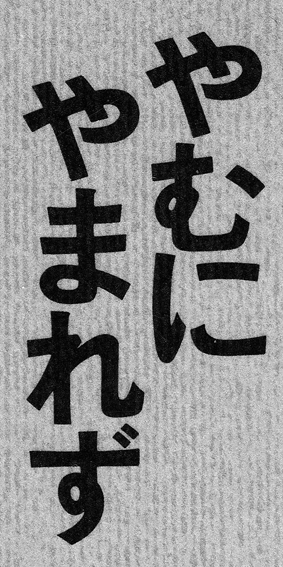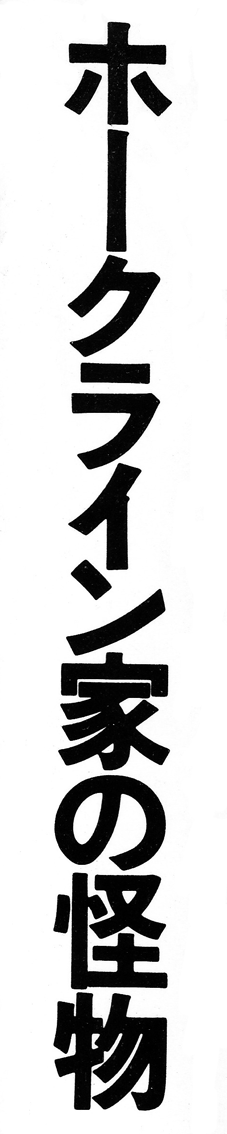
かな民友ゴシック
ああ、こまった。
いったいなにがこまるのかって、この書体についてかこうとするとき、〈かな民友ゴシック〉の名前だけを挙げるのはひどくきまりが悪いからだ。
私は今まで〈かな民友ゴシック〉について写研の写植書体だという程度の知識しか持ち合わせていなかったのだが、もともとは民友社という活版製造所の活字書体を写研が写植化したものだそうだ。ちなみにモリサワにも同じ民友社の名前を冠した写植書体がある。
しかし現在、巷に流通しているこれとよく似た文字は〈ヒラギノ角ゴオールド〉という名前のデジタルフォントで、それは民友社とはまた別の、藤田活版製造所の金属活字を見本に字游工房が制作した〈游築初号ゴシックかな〉と、以前からあった〈ヒラギノ角ゴシック〉の漢字を組み合わせて、大日本スクリーン製造からリリースされた新しい書体だという(ああ、こまった。なんのこっちゃである)。
こんなややこしいことになったのも、字形というものの宿命だなあと思うのだが、民友社、また藤田活版製造所のいずれも、明治時代に日本の活版印刷技術を牽引した東京築地活版製造所の活字母型を継承しているためらしい。
このとぼけた味わいをもつゴシック体が、時空を超えて同質性を保っている、という事実は、日本の活字書体のデザインがいかに極められていたかということの証明にも思えてぐっとくる。
勿論、読者にとっては文字の血統や素性を知る必要などないし、目の前で組まれたものがすべてだ、とも思う。
だから正直に告白すれば、私は、この書体に対して、まるでサンドウィッチマンのようなイメージをもっていた。目立つ図体のわりに肩身がせまそうというか、一歩引いている、というか。
活字だったころの名残りというべきか、文字の全体に圧がかかったような密着感のせいかもしれない。
その印象はまさに、いまにも具がこぼれおちる寸前のサンドウィッチを連想させる。それも上品につまむようなものではなく、質素だけれど、きちんとおいしいものを豪快にはさんだ、かたいパンのサンドイッチ。日々の糧を得るために働く労働者の手で、急いでほおばりたくなる。
関川夏央の『やむにやまれず』を読んだとき、この感じにはどこかで見覚えがある、と思ったら『ぼのぼの』(いがらしみきお)だった。
ふきだしのセリフやモノローグはすべて作者の手書きだが、タイトルにつかわれている見出しの文字が〈民友かなゴシック〉である。
「こまるのはそのうちなのに もうこまってる」と言うぼのぼのには、親近感を抱かずにいられない。
「生き物は生きてる限り絶対こまるんだよ。こまらない生き方なんか絶対ないんだよ。そしてこまるのは絶対に終わるんだ。どうだ、少しは安心してこまれるようになったか」というスナドリネコさんの言葉も大好き。
ふつうこまっているときは、こまった状態そのものではなく、そうなった原因や結果の方に気をとられがちだけれど、この文字でかかれたタイトルをみていると、こまった気分というのは、確かにこういうかたちをしてるよなと思う。
この書体をえらんだひとは、なんでそのことを知っているんだろうと思う。
リチャード・ブローティガンの『ホークライン家の怪物』は、本文や発行年をみると活字の時代につくられた本なので、これが〈かな民友ゴシック〉のルーツといえるのかもしれない。
物語が始まっても、怪物はなかなか姿を現さない。
でも、私は、その怪物には名前がないことを知っている。目立つ図体のわりに肩身がせまく、世間からは一歩引いて、やむにやまれず身をやつしていることを知っている。言葉では把握できない感情を抱えて。
私はたぶん、怪物の正体を知りたいのではなく、与えられた印象を確かめたくて本を読むのだ。想像が当たっているかどうかは、この際あまり重要じゃない。
そういうのは悪くないな、と思う。世のなかにはきっと、どこかに同質のものが存在して、それは誰かとわけあえるものにちがいないと、一瞬でも、そう信じられることは悪くない。
私はそのことを文字の力に教えられた。
おかげで、大人になった今、「少しは安心してこまれるようになった」と思っている。